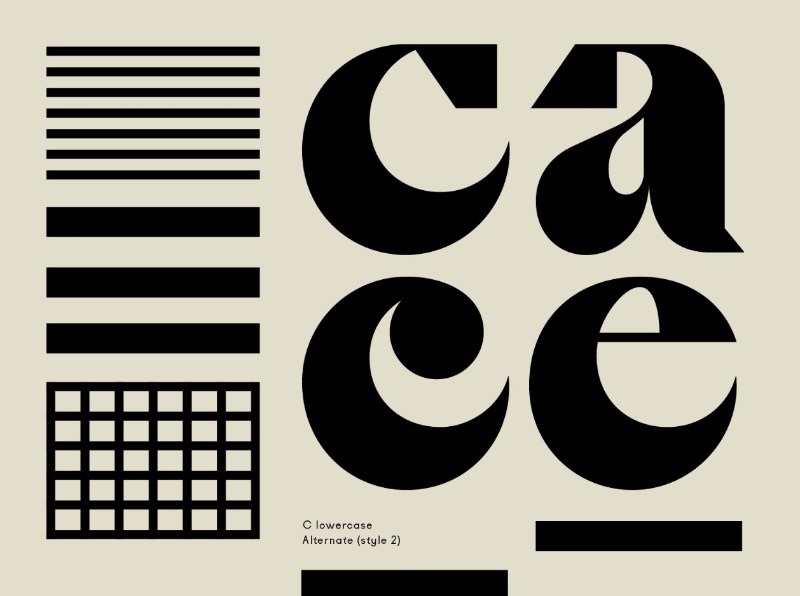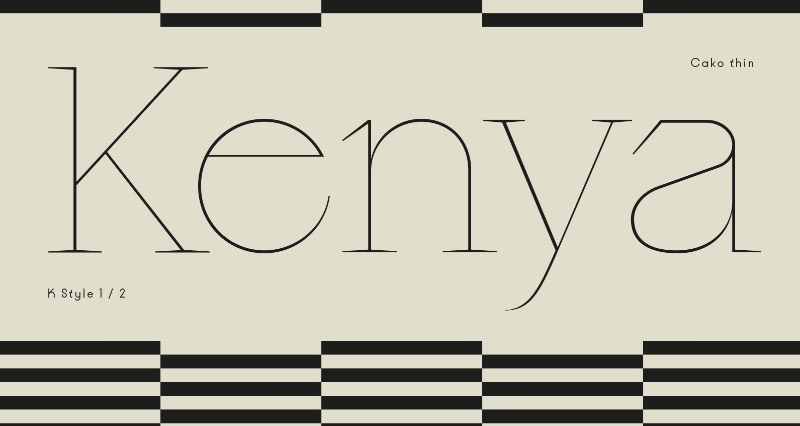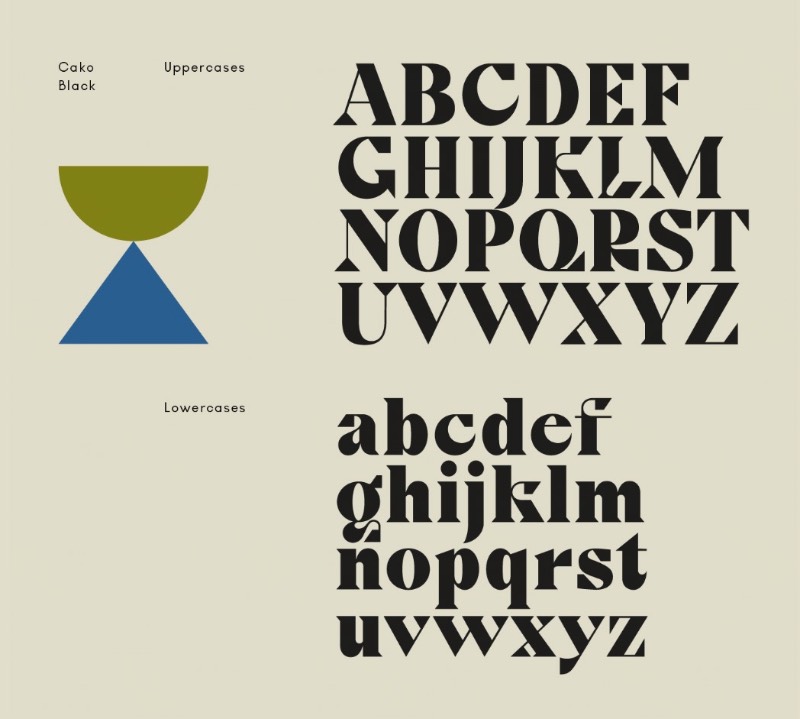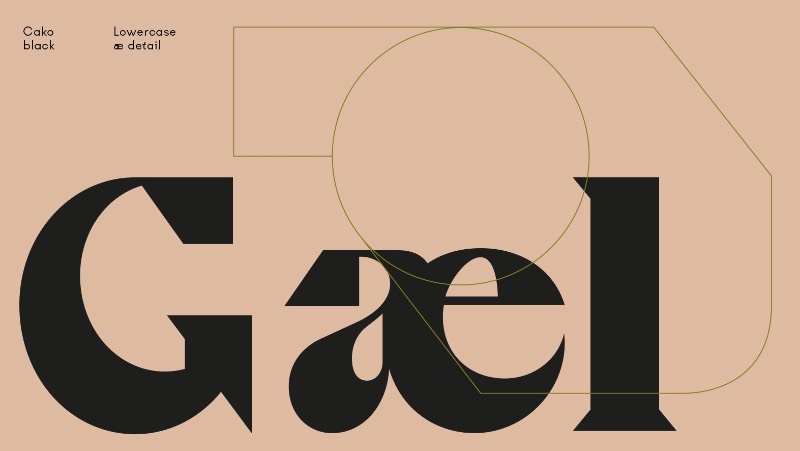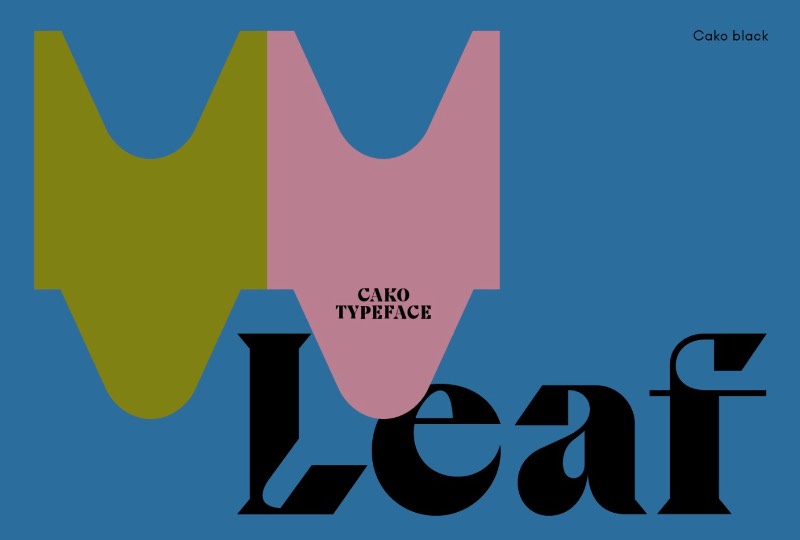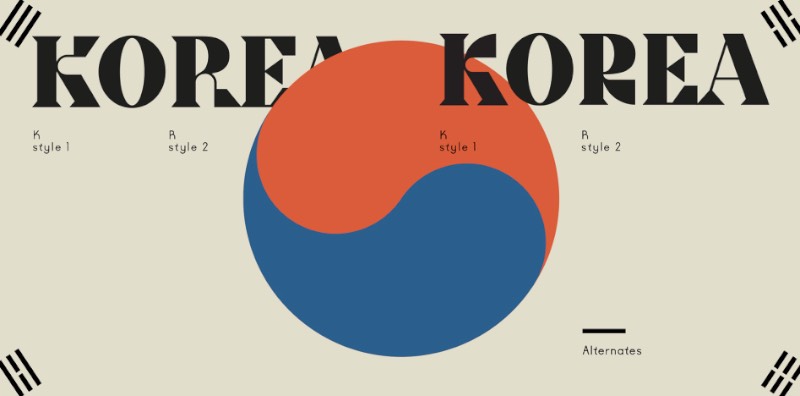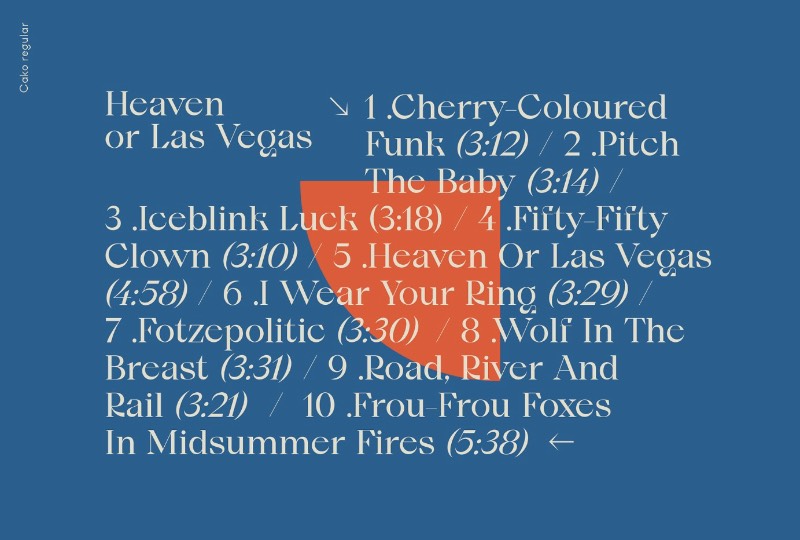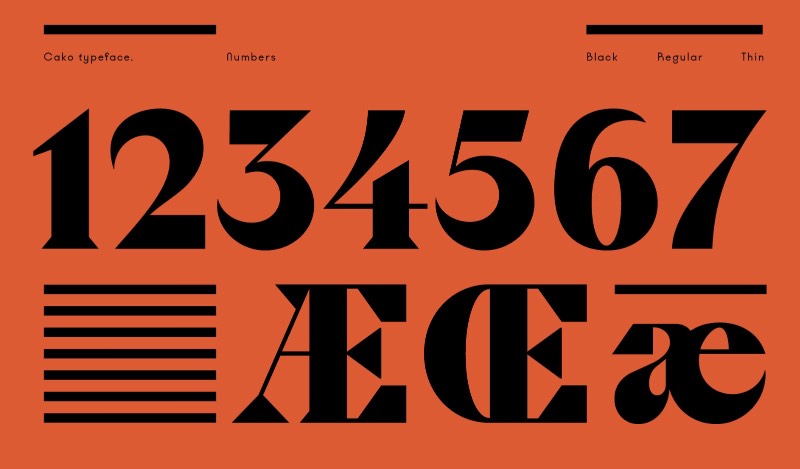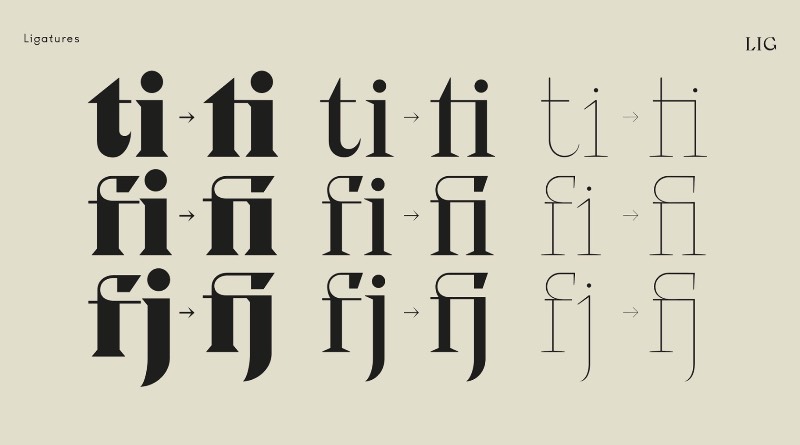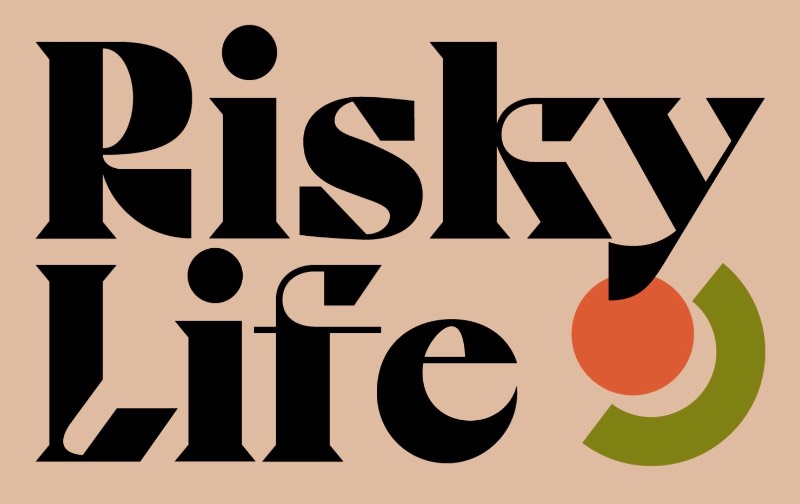
Cako: Uma fonte cheia de estilo criada por Jeremy Schneider
A Cako é uma família tipográfica que foi projetada por Jeremy Schneider em meados de 2019, direto de Paris. O que me chamou a atenção nessa fonte foi a forma quase única com a qual o designer trabalhou as formas e serifas de suas letras. Repletas de alternativas de estilos diversos e que, mesmo assim, continuam fazendo parte do conceito inicial dessa fonte.
A Cako vem ao mundo em três pesos diferentes: black, regular e thin; que oferecem soluções visuais diferentes para problemas de comunicação diferentes. Além disso, é interessante observar com o desenho das letras dessa fonte são caracterizadas por um contraste grande entre seus detalhes. Com terminais afiados que combinam muito com o alto contraste do design.
Além disso tudo, algo que me chamou a atenção nessa fonte foi a forma com a qual o designer Jeremy Schneider apresentou seu trabalho no Behance. Adicionando movimento a tipografia, você passa a enxergar suas formas de um jeito diferente. Somando isso ao movimento das cores e as outras animações que ele acrescentou no projeto, tudo fica ainda mais interessante.
Cako typeface was designed in 2019 in Paris by Jérémy Schneider. What makes Cako unique is its very graphic shapes of letters and serifs and its numerous stylistic alternates – giving the typeface a great rhythm. Cako has three contrasted weights, black, regular and thin, offering several degrees of impact. The drawing of Cako black is characterized by significant contrasts between thicks and thins, fine details and spiky terminals.
Cako é uma fonte cheia de estilo criada por Jeremy Schneider